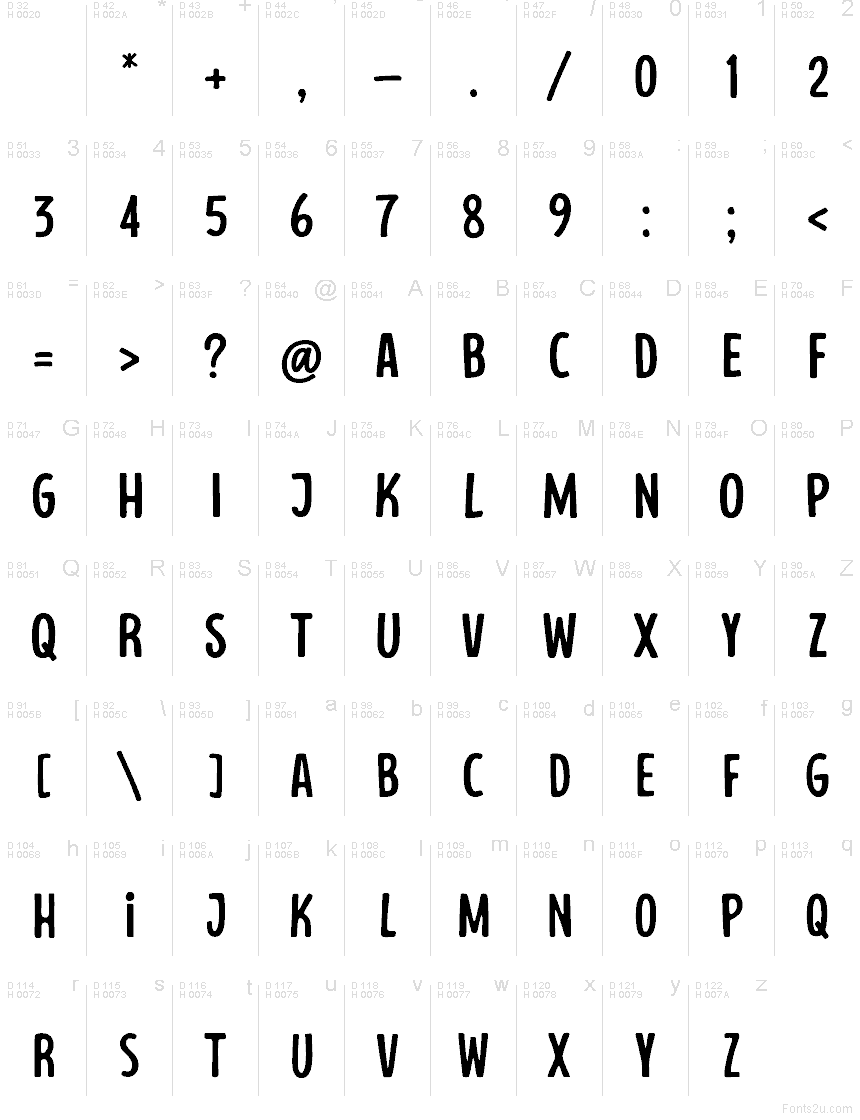
Make Things Sans, do Afkari Studio, é uma fonte display gratuita no estilo cartoon, com maiúsculas robustas desenhadas à mão e um ritmo descontraído. As letras parecem recortadas de blocos macios, com cantos arredondados, larguras irregulares e um aspecto levemente trêmulo que mantém o visual lúdico em vez de polido.
Ela encaixa naturalmente em capas de livros infantis, embalagens de snacks, pôsteres de festas, branding artesanal e posts alegres nas redes sociais, onde uma fonte gratuita com esse balanço artesanal pode carregar palavras curtas e títulos simples. Use-a para cartões de título, adesivos grandes ou iniciais estilo monograma quando quiser que as letras sejam amigáveis, ousadas e intencionalmente um pouco bagunçadas.